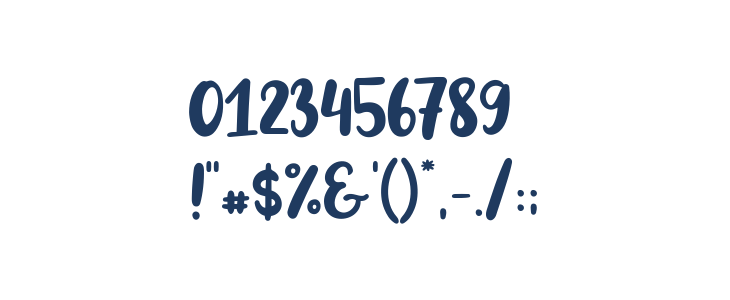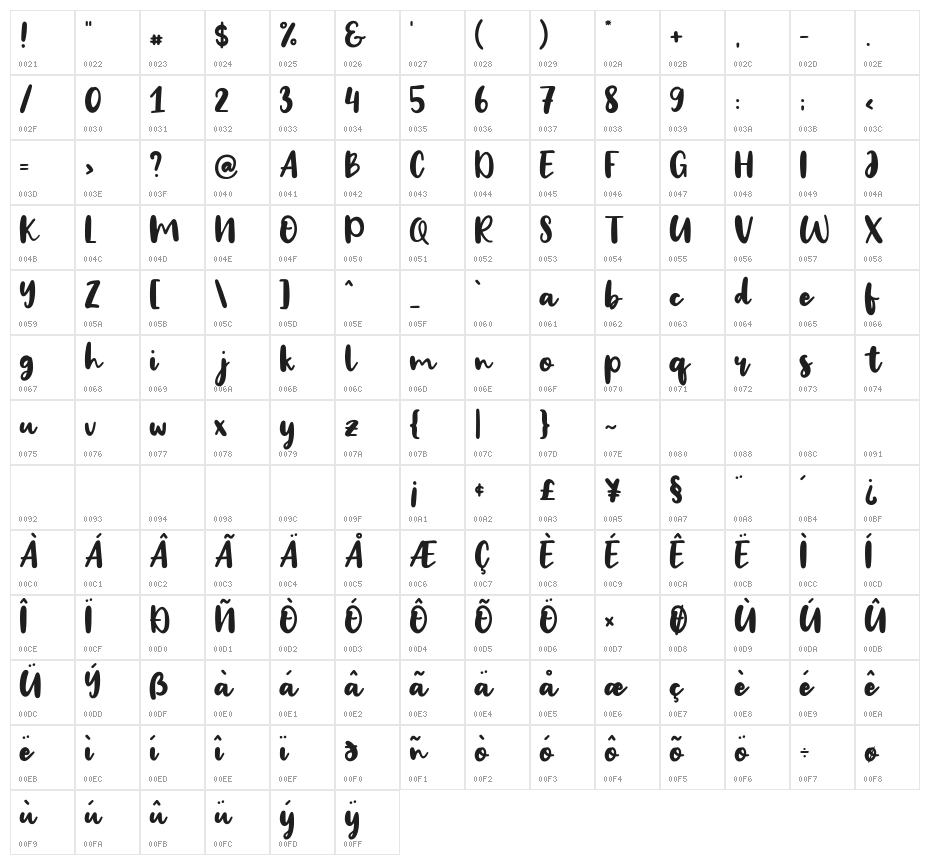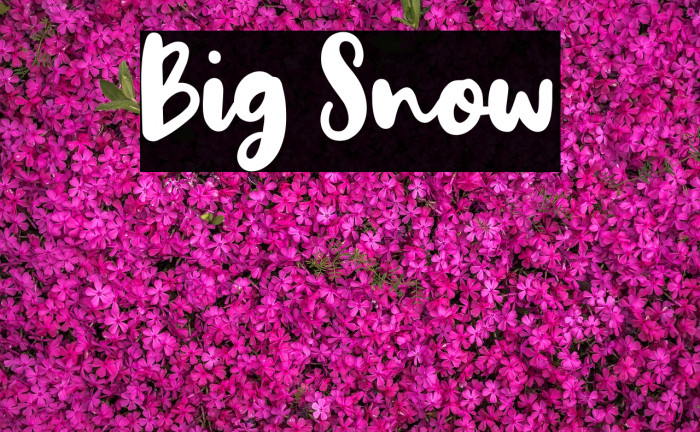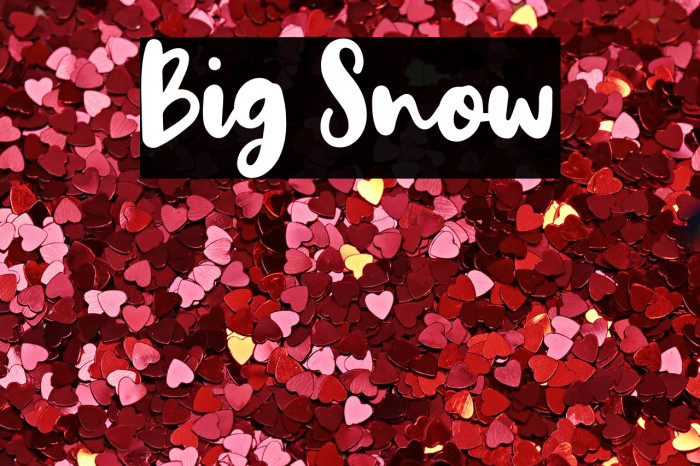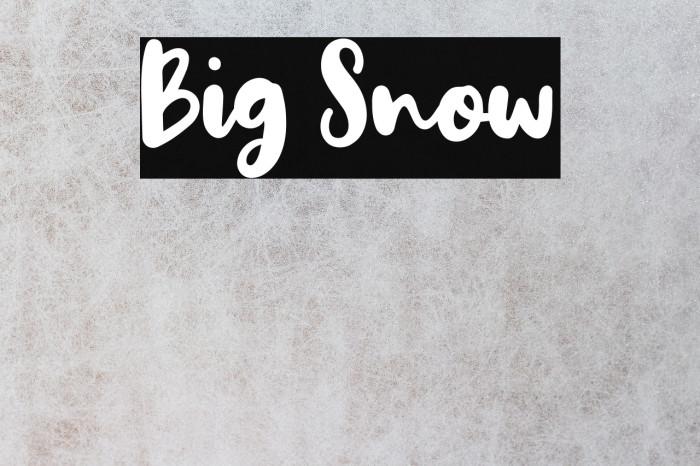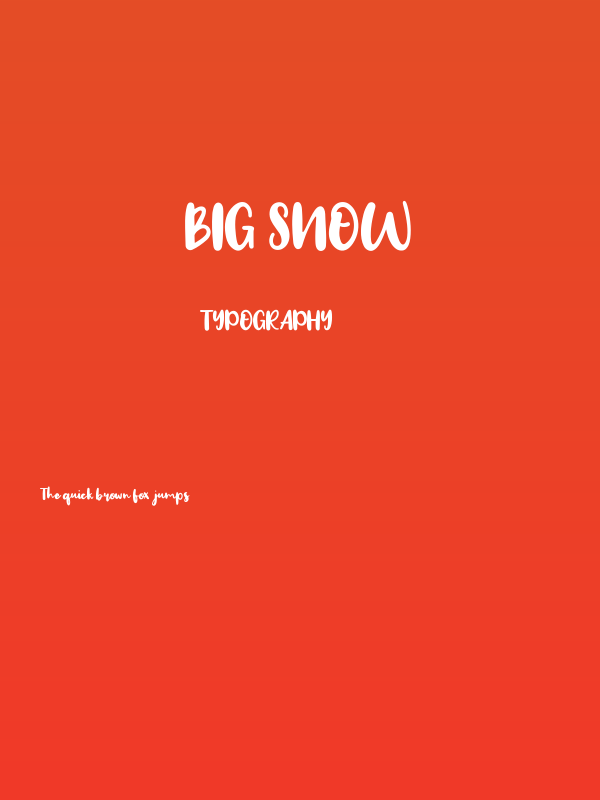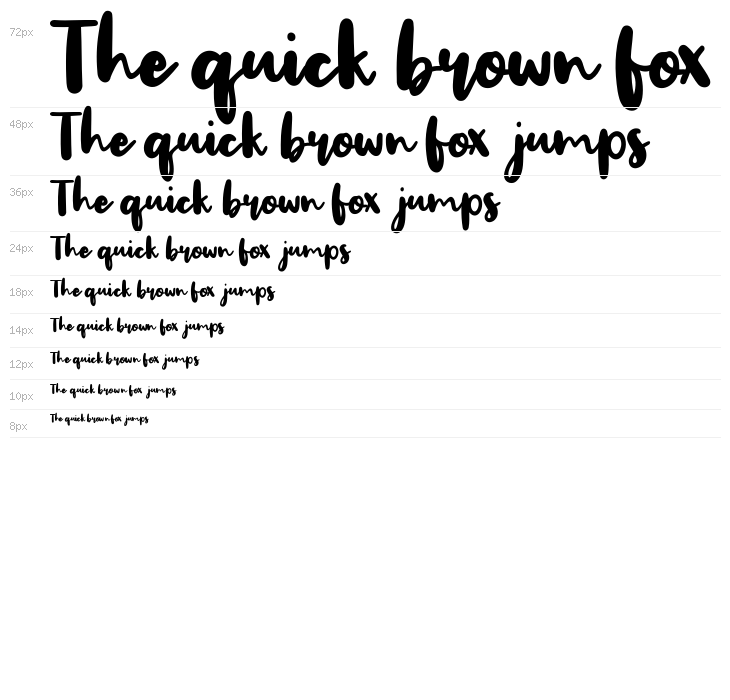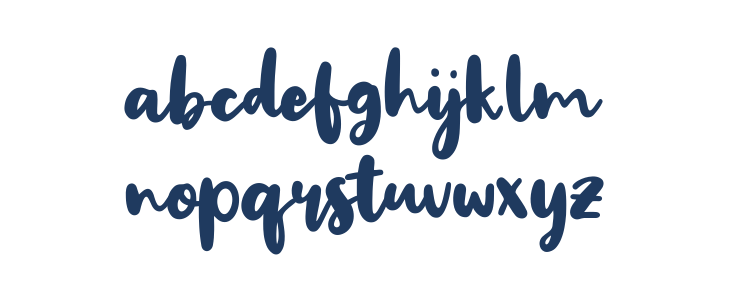
Big Snow Font
| Gesamtstil | Playful, Modern |
| Anwendungsfall | Logos, Headlines, Invitations |
| Vorgeschlagene Projekte | Ideal for greeting cards, invitations, playful branding, and social media graphics. |